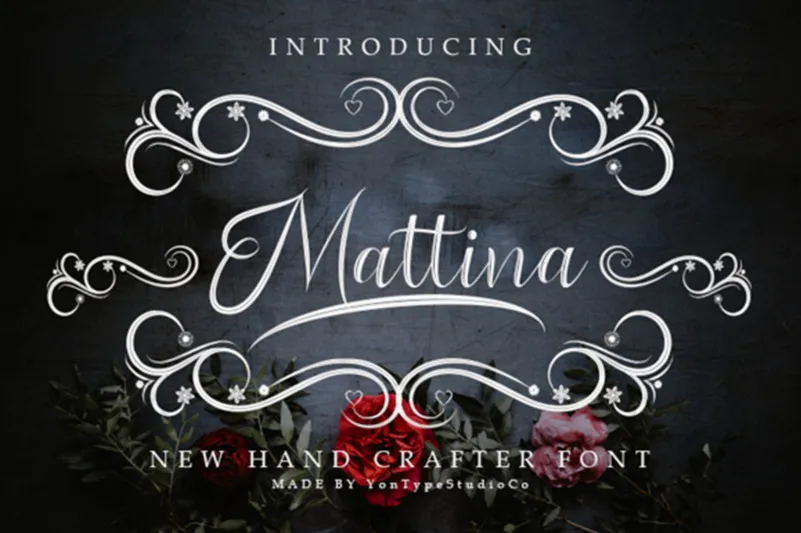
Mattina Script Font – Download Grátis
Olá! Estamos muito felizes por ter a oportunidade de apresentar à vocês uma nova fonte cíliada chamada Mattina Script Font. É um tipo de script leve e elegante, perfeito para dar aquele toque especial em seu projeto. Mattina Script Font é ideal para uso em estampas de água-marinha, como marcas e selos, bem como nas identidades visuais das marcas e no design de invitations de casamento. É uma fonte atraente que enriquece qualquer visual com suas curvas delicadas e traços suaves. Seja para assinar seu nome em um anúncio de moda ou para dar um toque de elegância ao seu logotipo, Mattina Script Font é uma escolha perfeita. E o melhor: ela oferece um ar fresco e suave, ideal para qualquer projeto que você esteja criando. Com certeza, a adição desta fonte a seu arsenal será um passo importante em sua jornada de criação!